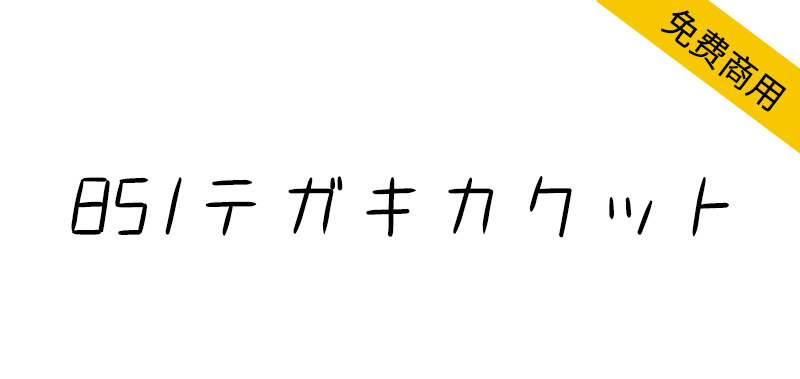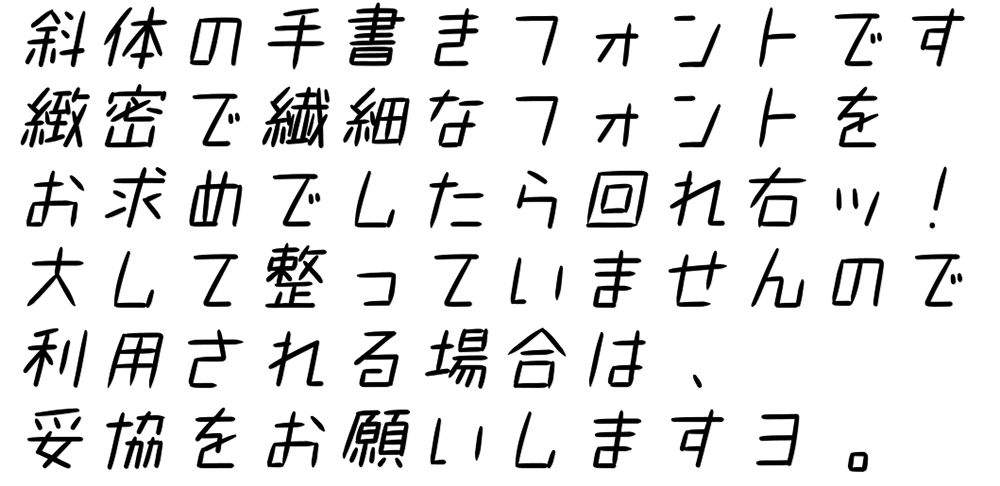
851斜书体(851テガキカクット)是由日本设计师 8:51:22 pm设计的一款手写意大利斜体风格日文字体,当前字符数:4964个字符(不包括空格)
对应文字:平假名、片假名、拉丁文字(英语)、数字、符号(少许)、汉字(常用汉字+2200字左右)
注意:这款字体适用于繁体和日文,不适用于简体中文,容易缺字。